見てわかる、迷わず決まるフォントのアイデア マネするだけでセンスのいいフォント
インプレスグループでIT関連メディア事業を展開するインプレスは、「見てわかる、迷わず決まる」シリーズ第二弾として、ingectar-e(インジェクターイー)著書による、、チラシ、ポスター、WEB、動画などのあらゆるデザインシーンのフォント選びで悩まないマネするだけで今すぐオシャレなフォントを選べる本「見てわかる、迷わず決まるフォントのアイデア マネするだけでセンスのいいフォント」を2021年10月19日(火)に発売した。
その大人気書籍のコンセプトを踏襲した『見てわかる、迷わず決まる』シリーズ第二弾として、「フォント」をテーマにした『見てわかる、迷わず決まるフォントのアイデア マネするだけでセンスのいいフォント』を発売した。
「見てわかる、迷わず決まるフォントのアイデア マネするだけでセンスのいいフォント」では様々なデザインシーンを想定した書体・センスのいい組み合わせを紹介している。
ナチュラル・ポップ・シンプル・エレガント・シーズン・ジャパニーズ・ビジネスの7カテゴリーで構成されており、様々なデザインシーンで活用できるアイデアを収録。「可愛い感じのデザインを作りたい」と作りたいイメージからフォントを選ぶことができる。
紙面は1見開きごとに、テーマに沿ったフォントの組み合わせがわかる構成となる。
フォントはメインフォント・ベースフォント・アクセントフォントの3種類の役割に分け紹介しており、紙面の組み合わせをそのままマネするだけでセンスのいいフォントが選べる内容となっている。
また紙面にはデザインサンプルもたっぷり収録しており、そのフォントを使ったデザインのイメージが掴みやすくなっている。
「見てわかる、迷わず決まるフォントのアイデア マネするだけでセンスのいいフォント」で紹介しているフォントは一部のフリーフォントを除いて、Adobe Fontで2021年9月に提供されているものとなる。
▼ナチュラルテイストのデザインに使いやすいフォントの一例
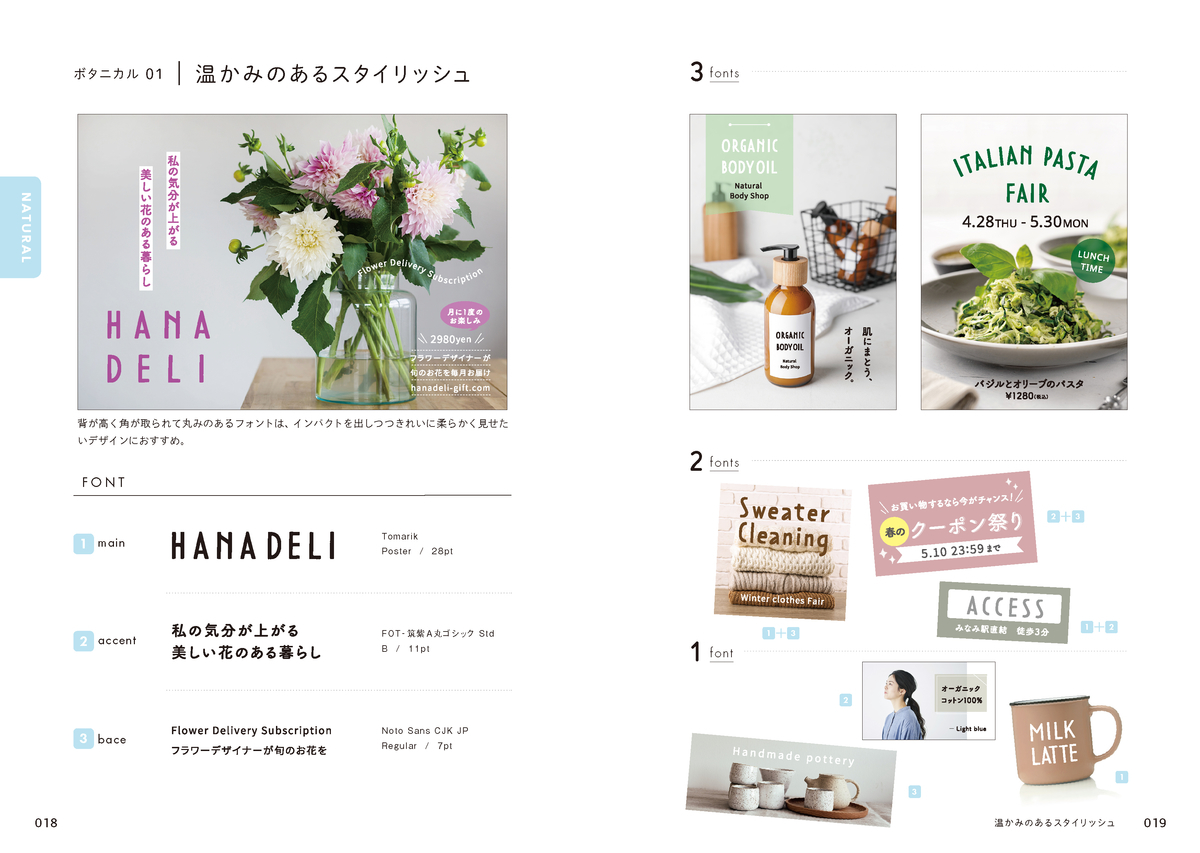
▼元気で明るいテイストでの事案に使いやすいフォントの一例
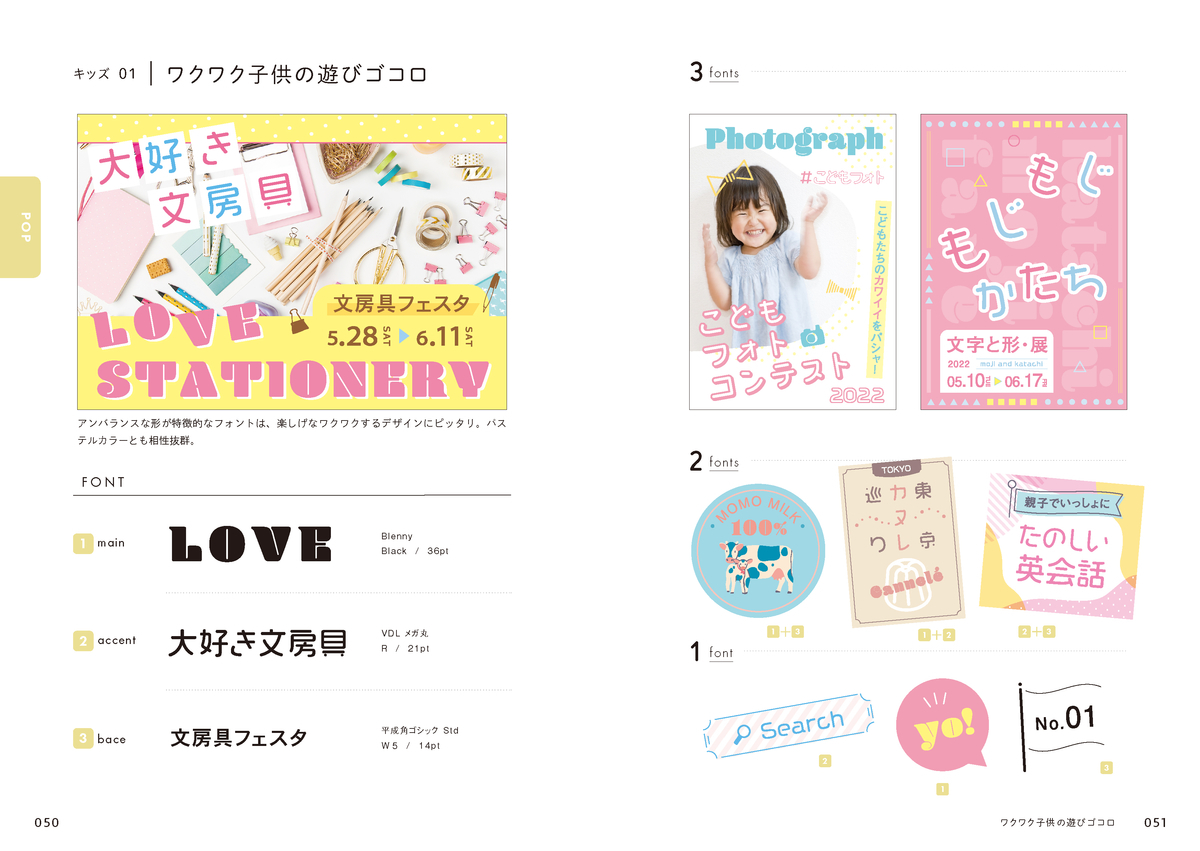
▼リクルートデザインと相性のいいフォントの一例
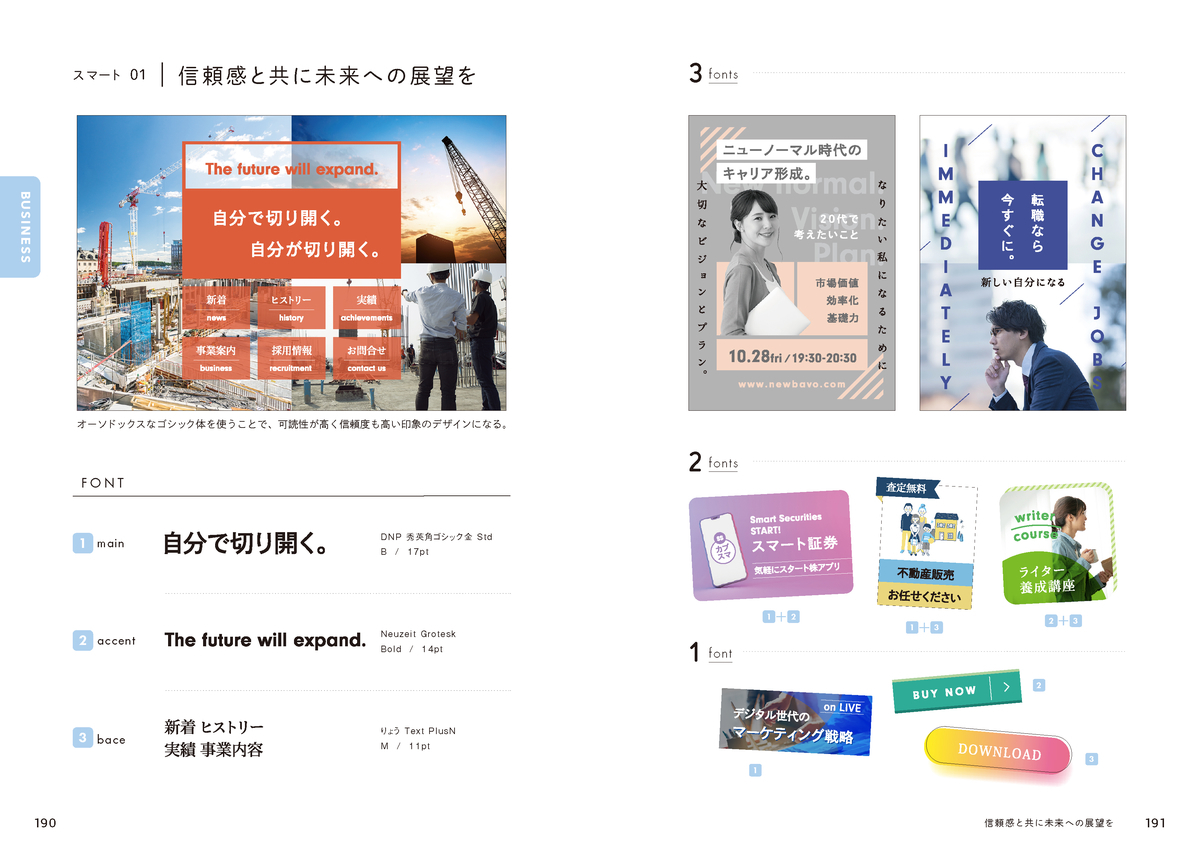
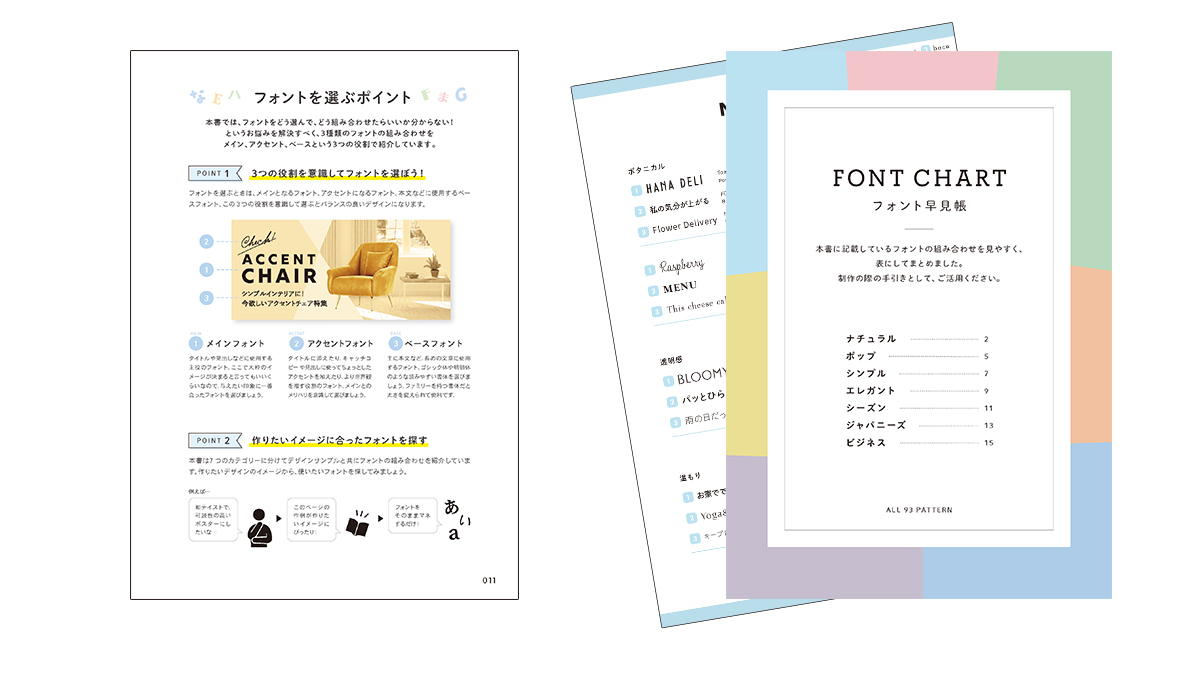
巻頭にはフォントの基礎知識やフォント選びのコツを解説しており、デザイン初心者や「ノンデザイナー」の方にも読みやすい構成になっている。
また書籍に収録しているフォントの組み合わせを一覧で見られる「フォント早見表(PDF)」も収録。
【「見てわかる、迷わず決まるフォントのアイデア マネするだけでセンスのいいフォント」に収録されているフォントのカテゴリー】
NATURAL:心地よいやさしさを
POP:ポジティブで心躍る印象に
SIMPLE:シンプルにスッキリ魅せる
ELEGANT:上品で優雅な雰囲気に
SEASON:楽しい、ワクワク、季節感
JAPANESE:艶やかな和風の世界感
BUSINESS:ビジョンやサービスを明確に